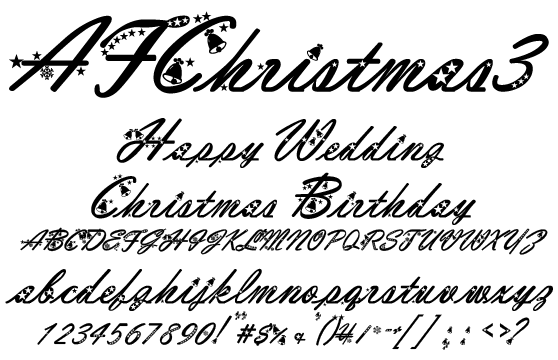
アンティークな筆記体 AFChristmas3
AFChristmas3
ファッション系ドキュメントに最適なAFscriptAntiqueにデコレーションしました。クリスマスやバースデーに利用できるフォントです。動画テロップ、Web Server へのアップロード、フォント共有サーバー利用、PDF エンベッド、印刷やロゴなど作成と登録、印影や彫刻、画像化後ソフトへのバンドルなど商用利用できます。